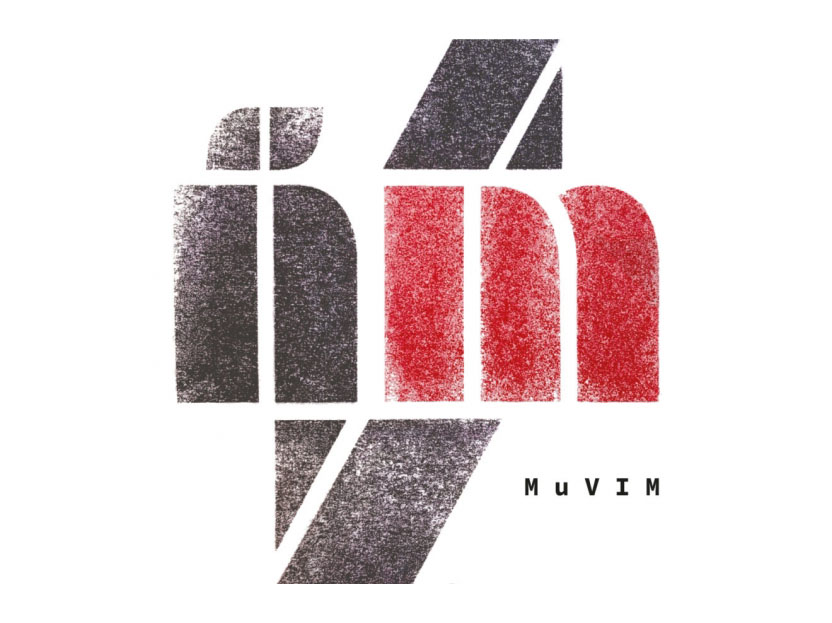
«El homenaje a una sola letra es un homenaje a toda la cultura».
El Museo Valenciano de la Ilustración y de la Modernidad (MuVIM) presenta Tipografia’m, una interesante exposición dedicada a la tipografía, que se articula a partir de la letra eme para «reivindicar el papel formal de la letra en el diseño y el arte», comentan desde el museo, y agregan: «Aislando un carácter cualquiera de su contexto habitual (la palabra, la línea, el párrafo, la página…), pretendemos alejarlo del dominio de la lingüística y aproximarlo al terreno de lo visual, para intervenir en él como objeto puramente formal. Todo ello conseguirá dar mayor visibilidad a la labor de tantos diseñadores de tipos que, con su esfuerzo y talento, han otorgado un carácter especial y único a cada letra eme diseñada».
El catálogo de la exposición cuenta con un prólogo del experto en comunicación y diseño Joan Costa, autor de casi 50 libros considerados un referente fundamental en el ámbito académico y profesional. Una frase de su texto ha servido de punto de arranque creativo a la diseñadora Begoña Jordá para la configuración del cartel promocional de la muestra. A través de la técnica de transfer se ha construido una imagen tipográfica cuya protagonista es la letra eme, elemento referente de la exposición, y que combina a la perfección con la máxima de Joan Costa: «El homenaje a una sola letra es un homenaje a toda la cultura».